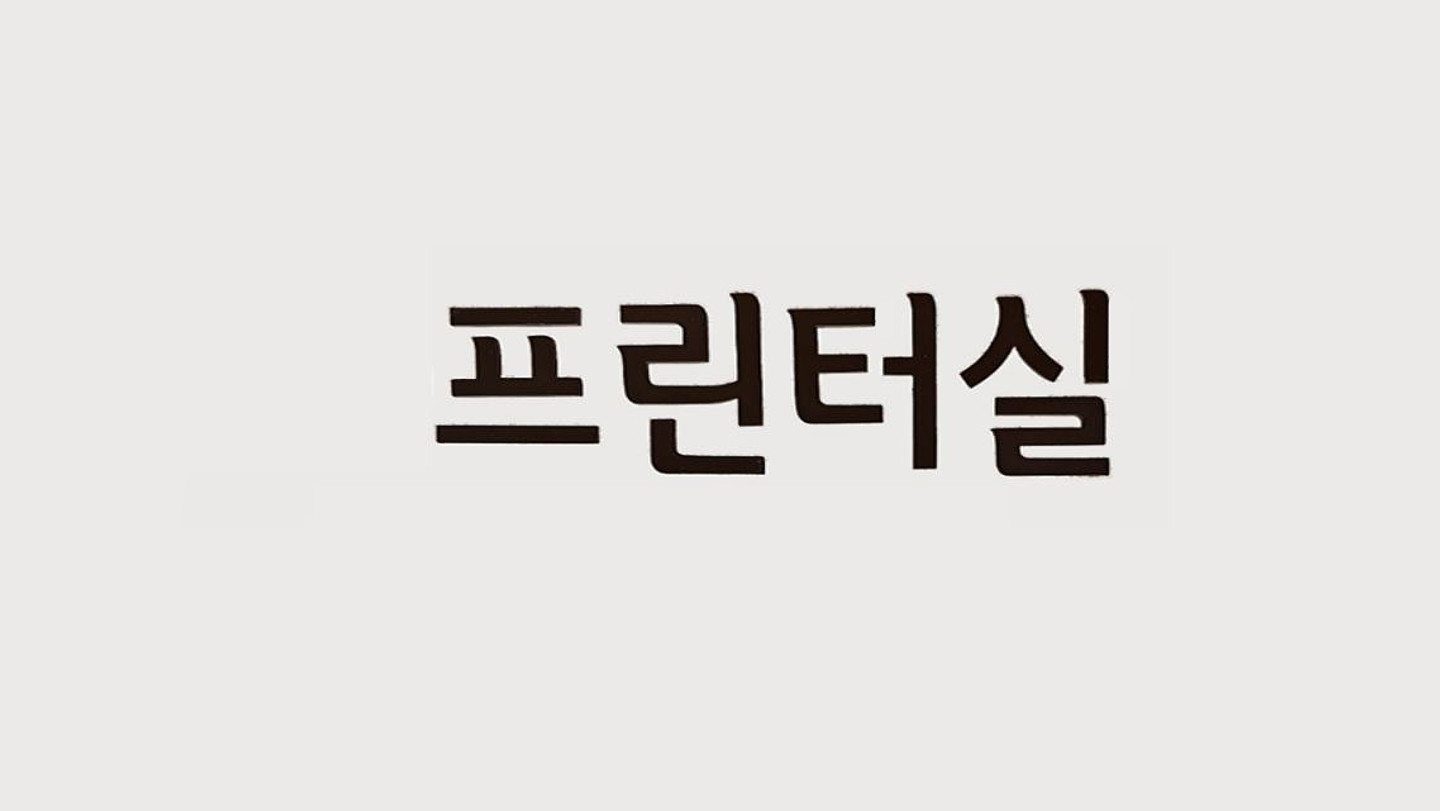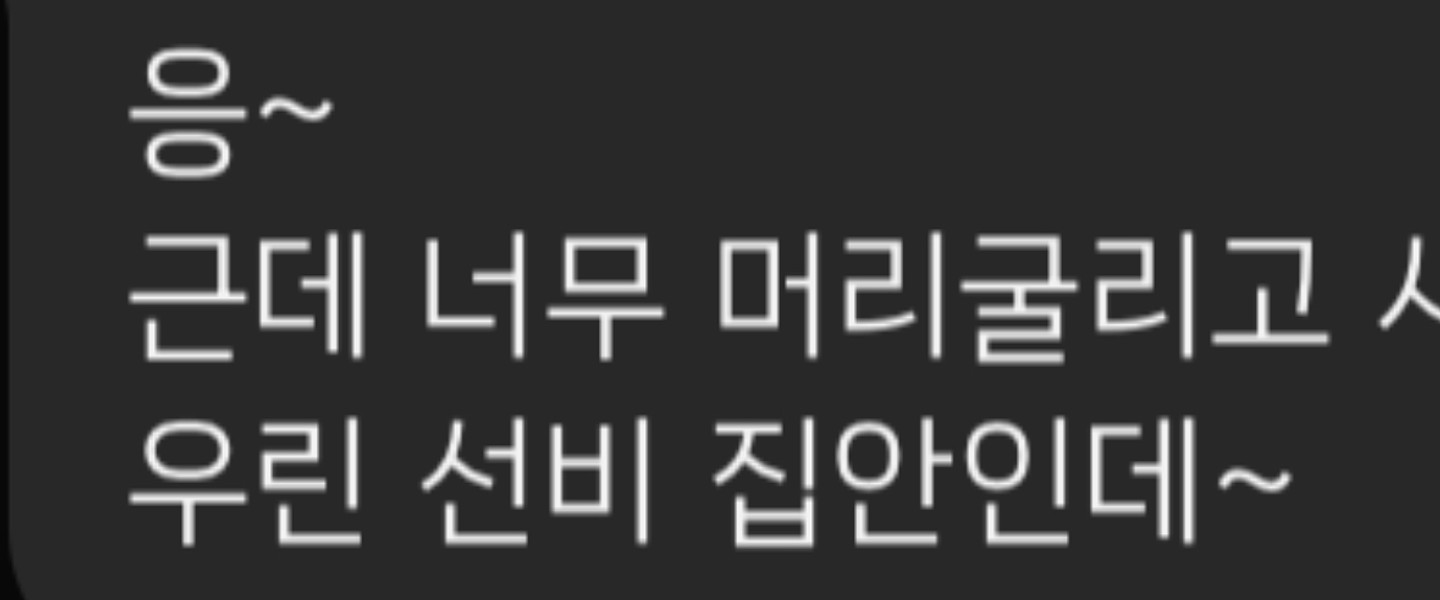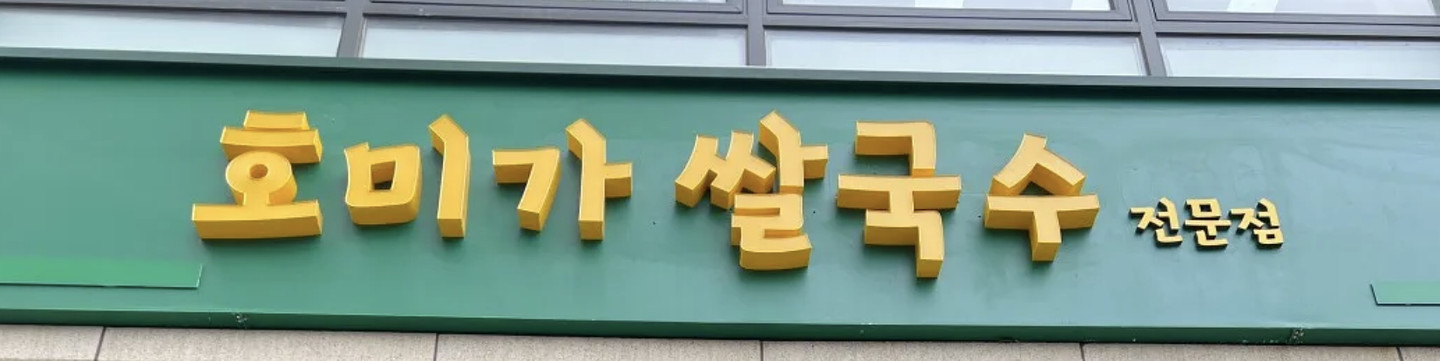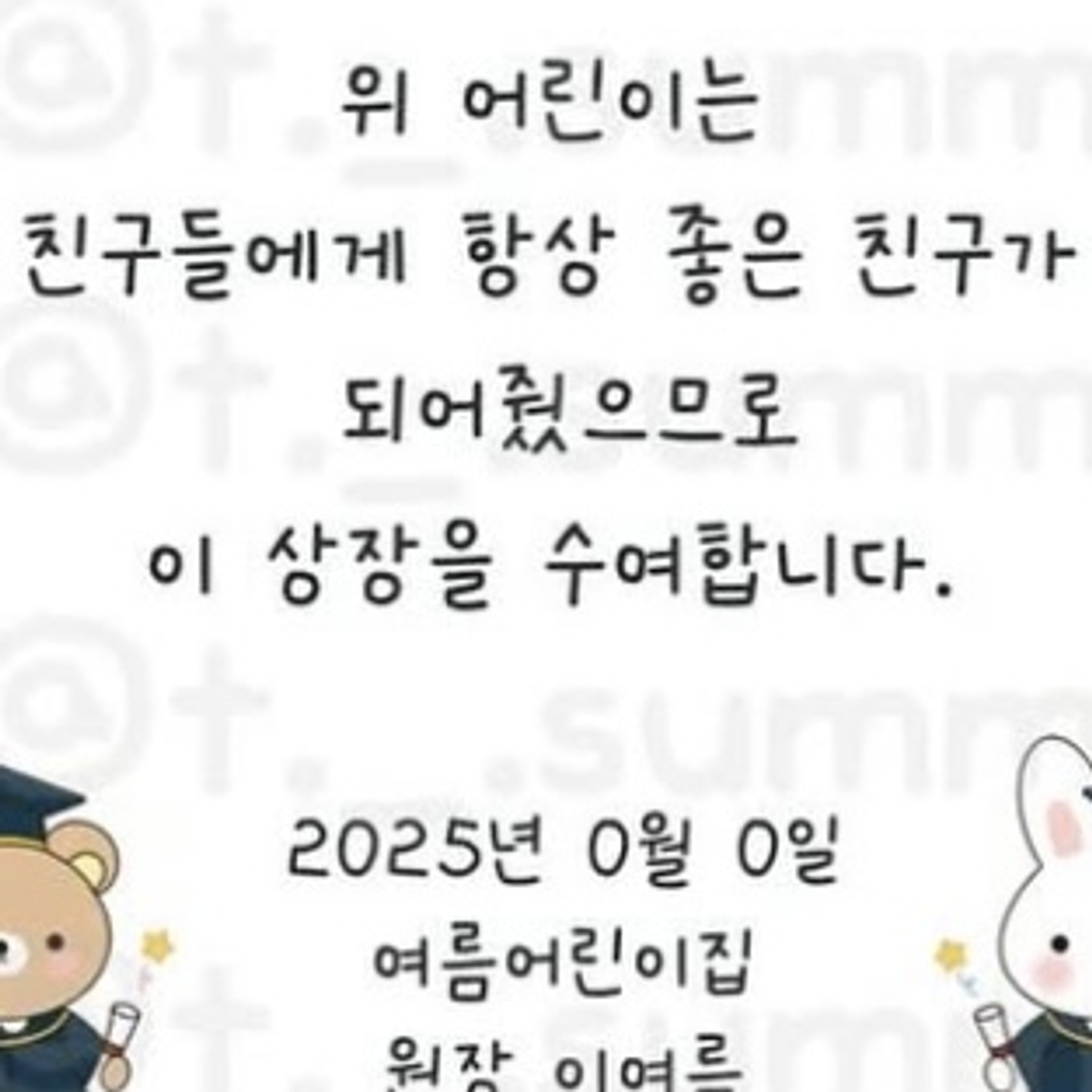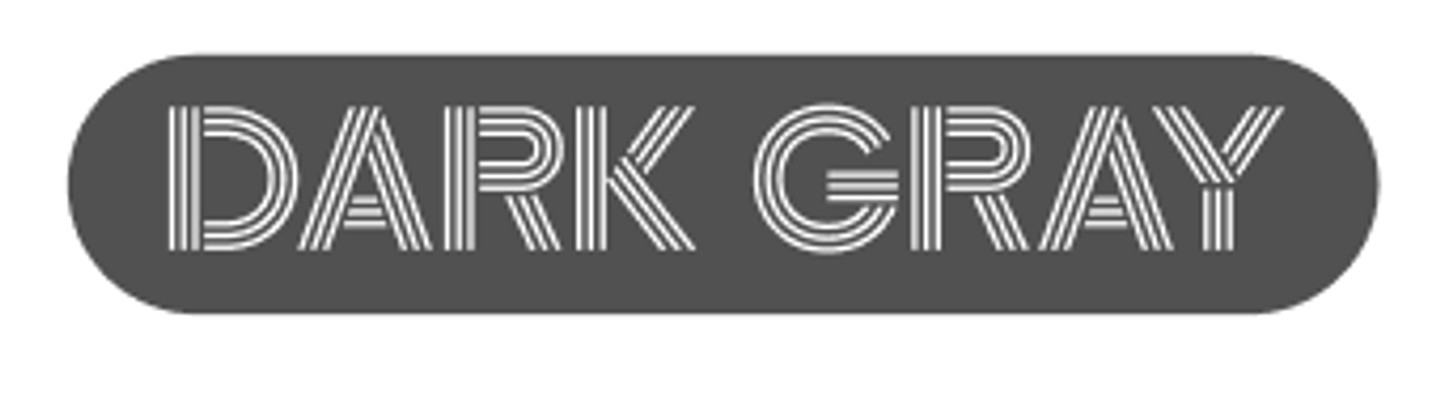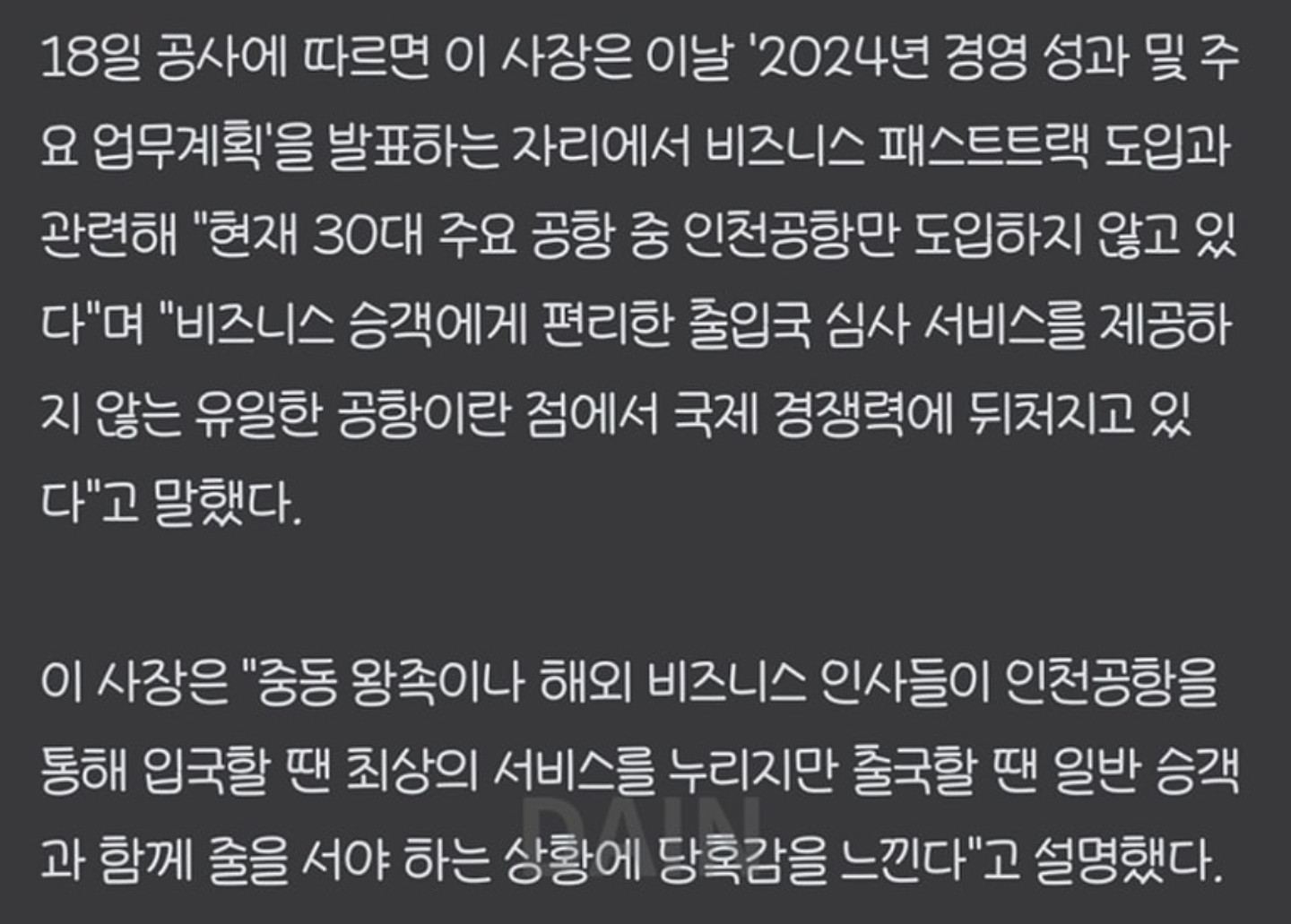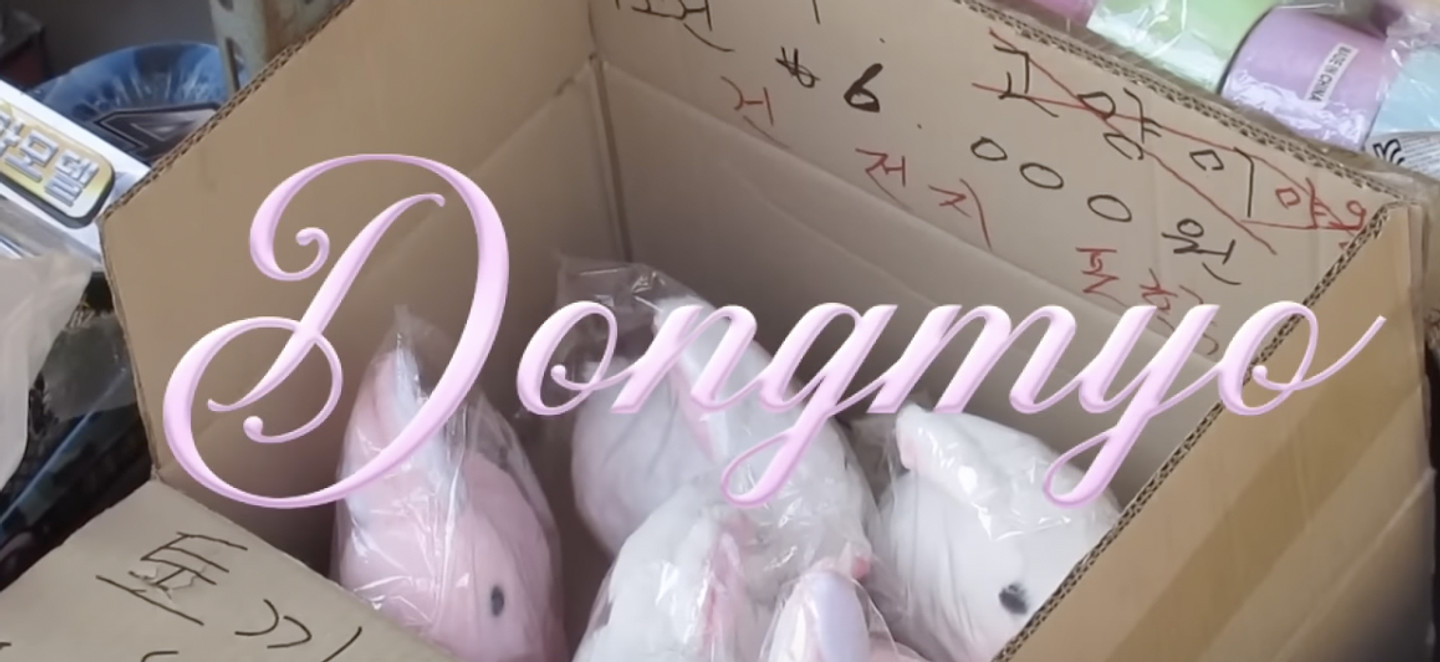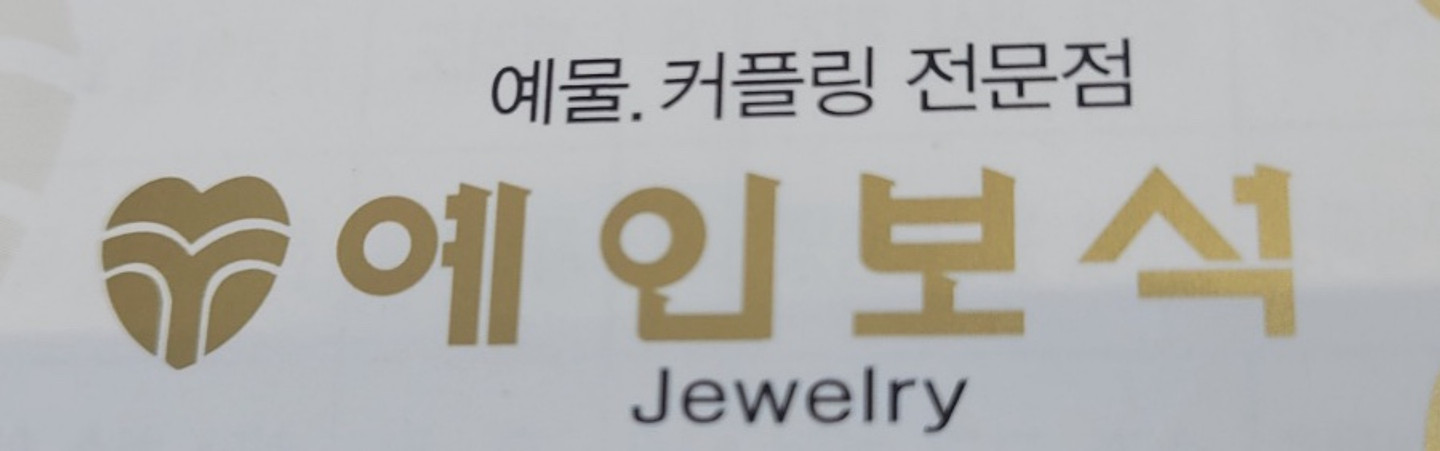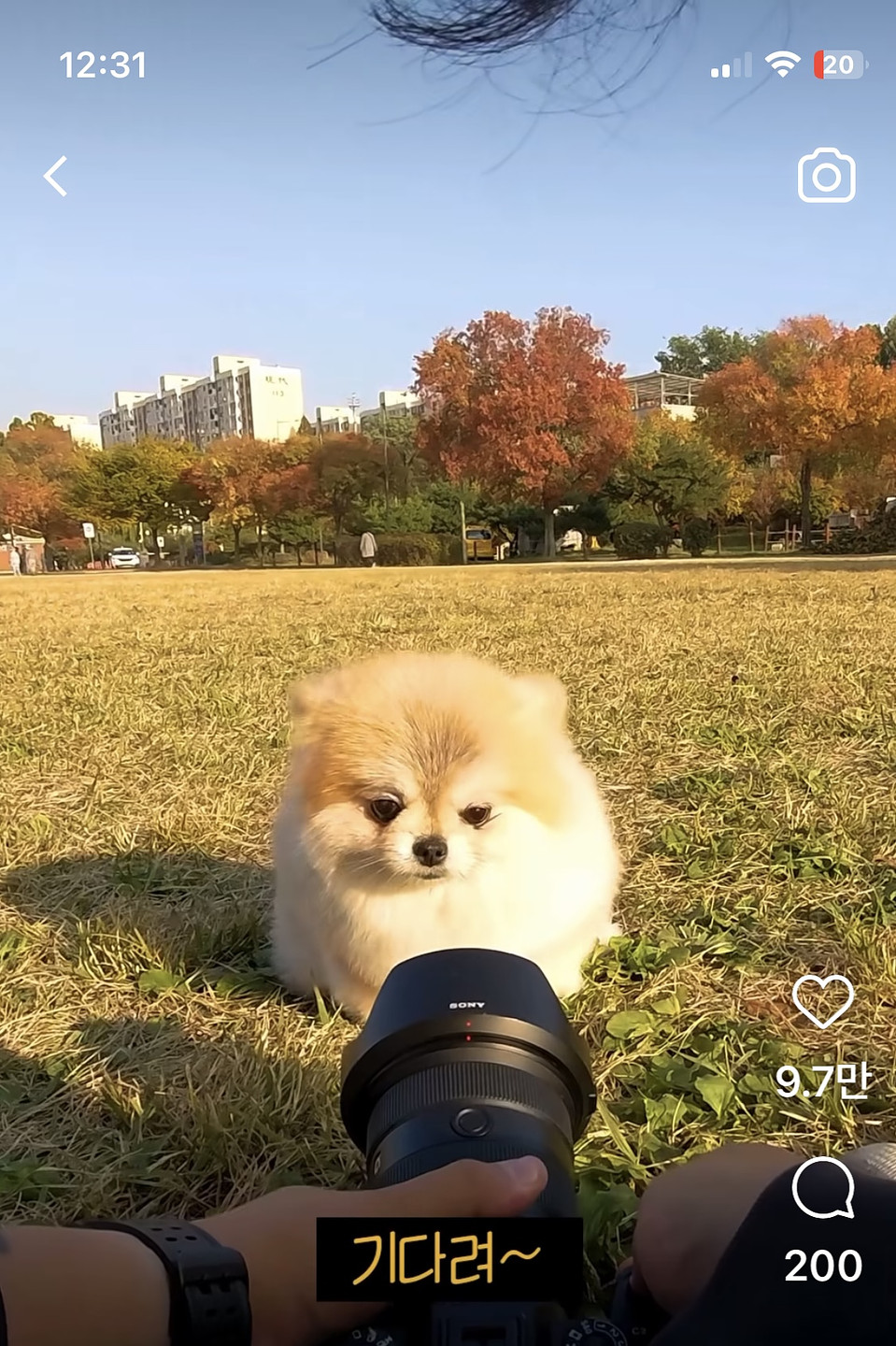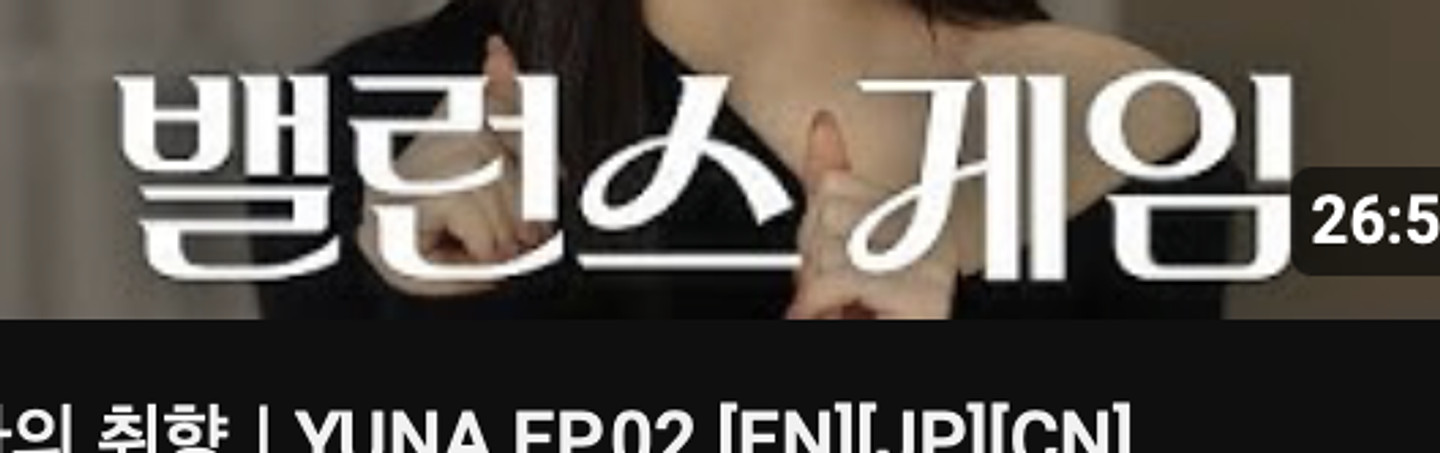
고수님들 부탁드립니다. 이거 무슨 폰트인가요? 비슷한 폰트라도 알려주세요. 제발요~~
마인크래프트 서버에 사용되던 폰트 입니다 약 7년 정도 된 걸로 알고 있습니다
무슨폰트인지 궁금합니다~~
준빵조교님 영상 폰트인데 뭘까요?
이 폰트 뭔가요,,!!!!
직화장아 무슨 폰트일까요?
무슨 폰트일까요? 제목용 폰트로 쓰고 싶은데 찾기가 힘드네요ㅠㅠ
폰트찾기에 돌려봤는데도 제일 비슷한게 클래식<인데 비교해보니까 다른 것 같더라구요... 레터링은 아닌 것 같길래 다른분들 도움을 받고 싶어 올려봅니다...!!
이 폰트 너무 궁금합니다 ,,,!!!
서체이름을 알고 싶어요
무슨폰트일까요???
여기서 어린이 멀미약 제품에 폰트 ㅁ멀까요? ㅠㅠㅠ 넘 궁금해요 ㅠㅠ
파란 동그라미 안에 있는 "이레" 는 무슨폰트일까요..? 캘리폰트는 찾기가 어려워요~
이거 무슨 폰트인지 아시는분 계실까요?! ㅜㅜ
무슨폰트인지 아시는분있나요?
PARMA 글씨와 밑에 작은 글씨 폰트명 아시는분 부탁드립니다 (좋은 주말 되시구요)
c가 정원인 이 서체 이름을 알고 싶습니다.
영어 폰트 어떤 것인지 궁금합니다!
무슨 폰트일까요 ㅠ
이름 좀 알려주세요 부탁 드립니다 ㅠㅠㅠ
영어로 된 폰트
가을에 듣기 좋은 마음이 편해지는 음악 혹시 무슨 폰트예요?? 감사합니다
U, A, L 끝에 살짝 꺽인 포인트가 예뻐요!! 꼭 똑같은거 아니더라도 저런 끄트머리 포인트 있는거 있음 좋겠습니닷
이거슨 무슨 폰튼지 궁금해요!
손글씨 같은 느낌의 폰트에요
어디서 많이 본것같은데 무슨 폰트인가요?
유튜버 지방쿸님의 영상에서 캡쳐한 자막입니다! 폰트명이 궁금합니다 부탁드립니다~~~!!^^ 감사합니다
무슨글씨체인가요???
이건 무슨 폰트인가요?
손글씨 같은데 무슨 체인지 아시는 분 계실까요?
이 폰트 도대체 뭘까요?ㅜㅜ 너무 궁금해요 인스타 스토리인데 인스타 폰트는 확실히 아니라서 ㅜㅜ
이게 무슨 서체인가요?
이런 옛날 영화 불법 자막같은 폰트는 이름이 뭔가요?
이거 무슨 폰트인가요?ㅠㅠ 아무리 찾아도 안나오네요..
이 폰트 궁금합니다 !!!
폰트이름이 궁금해요
궁금합니디
굴림체 같은데 너무 궁금해요!
이 폰트 아시는 분 있으실까요..?
100시간 무슨 폰트인가요?
이 폰트 무슨 폰트 일까요? 양평체인지 알았는데 아니네요 ㅠ
무슨 글꼴 입니까?
할인해 봄 어떤 폰트인가요? 폰트가 아니라면 기반으로 됐을만한 폰트나, 비슷한 폰트 있을까요ㅠㅗㅠ
마재성지 폰트 알수있을까요..
인스타에서 카드뉴스 썸네일 등으로 많이 쓰이는 폰트같은데 이거 무슨 폰트인가요?
폰트 뭔가요
파리바게트 글씨체 궁금합니다. 비슷한거라도 있을까요?
백예린 콘서트 포스터에 있는 글씨인데 폰트인가요 손그림인가요…?